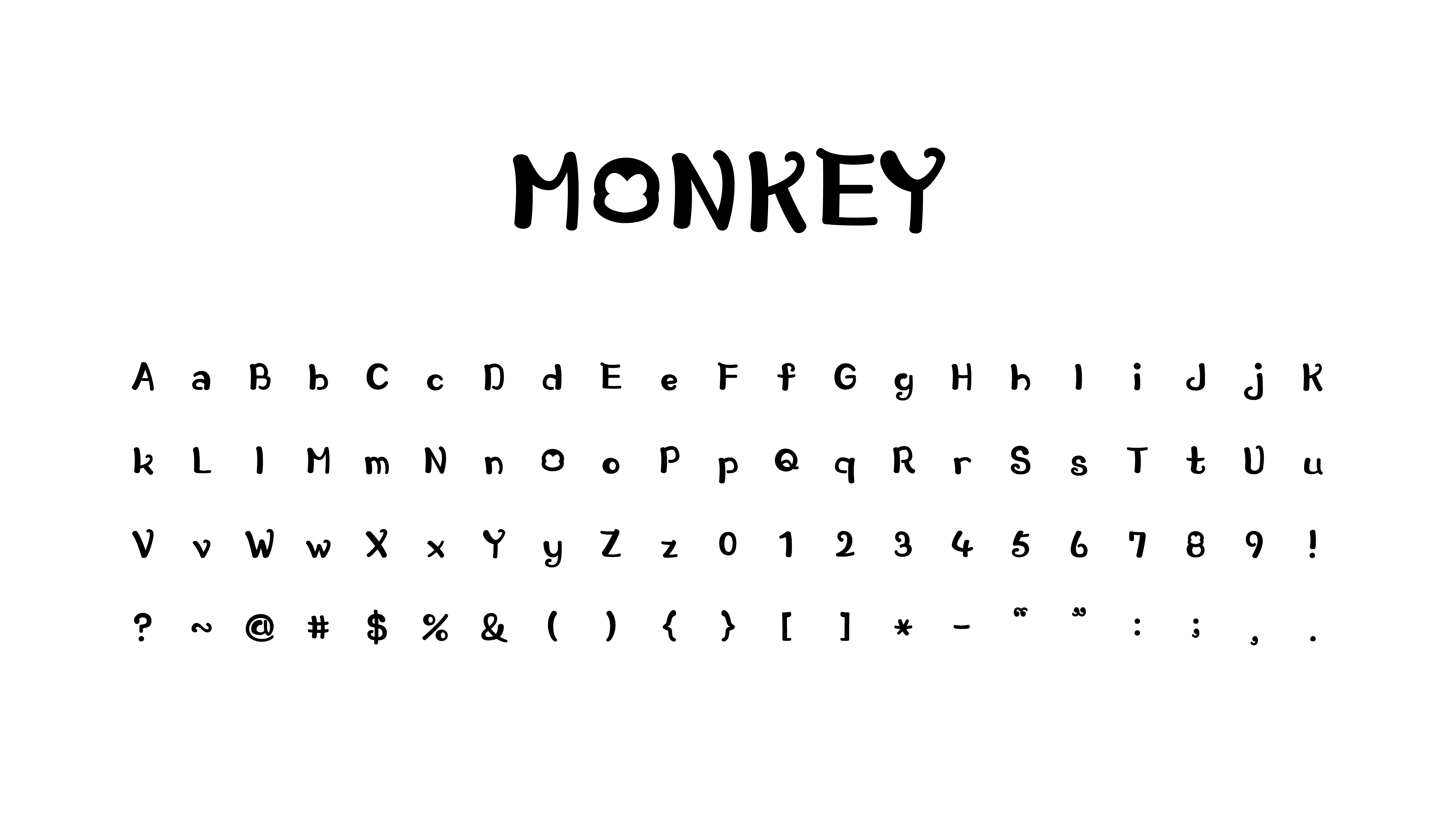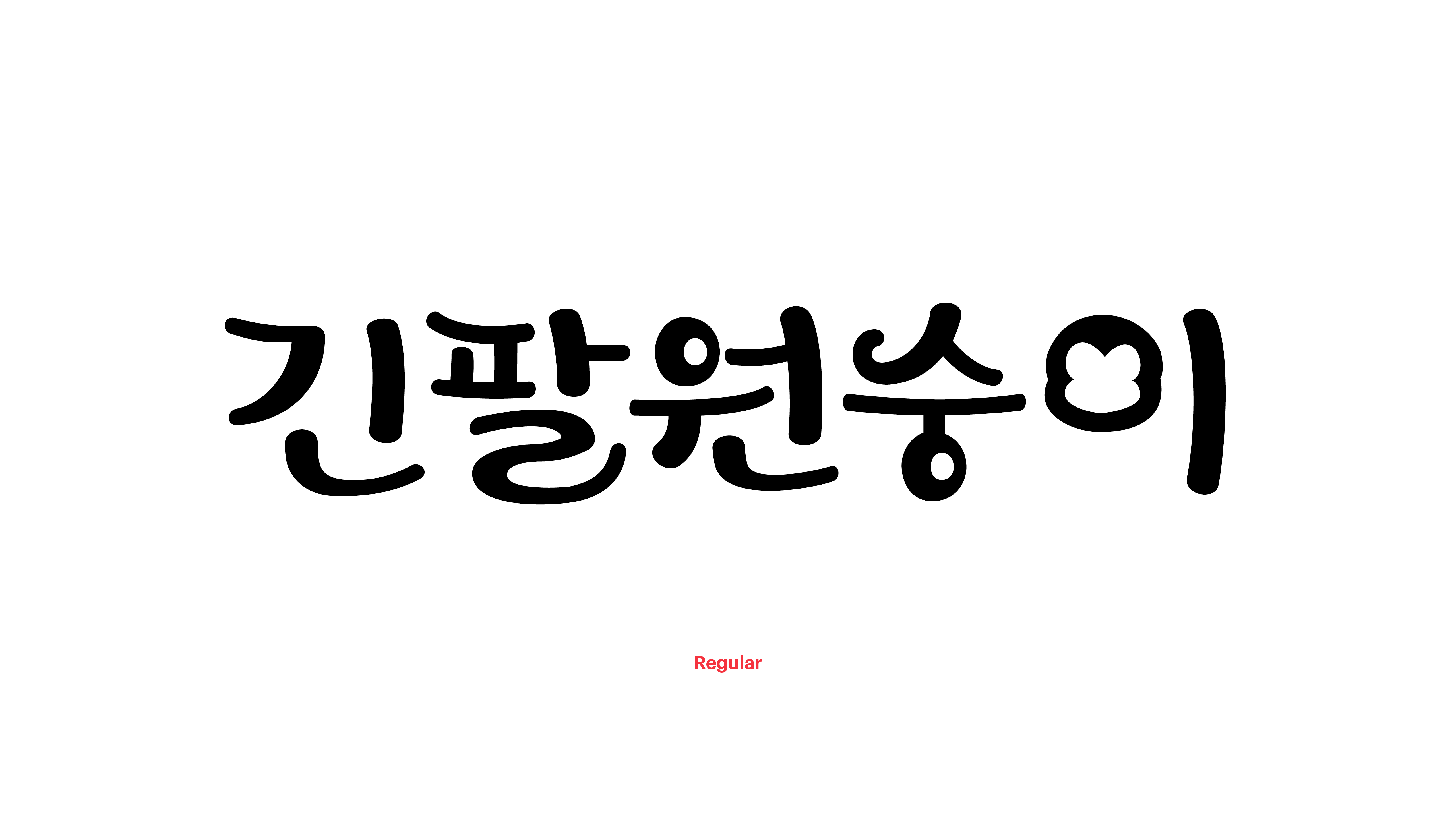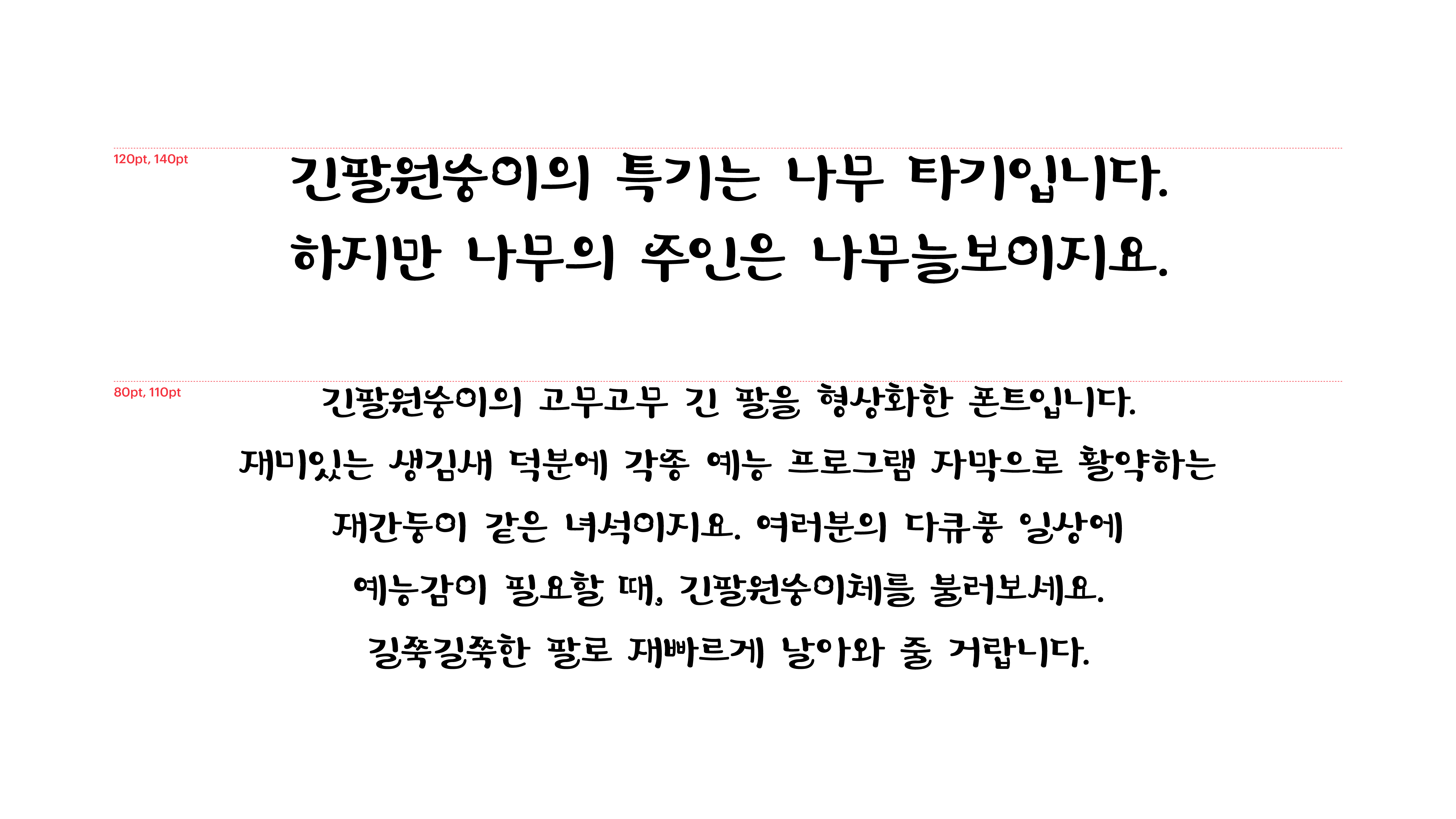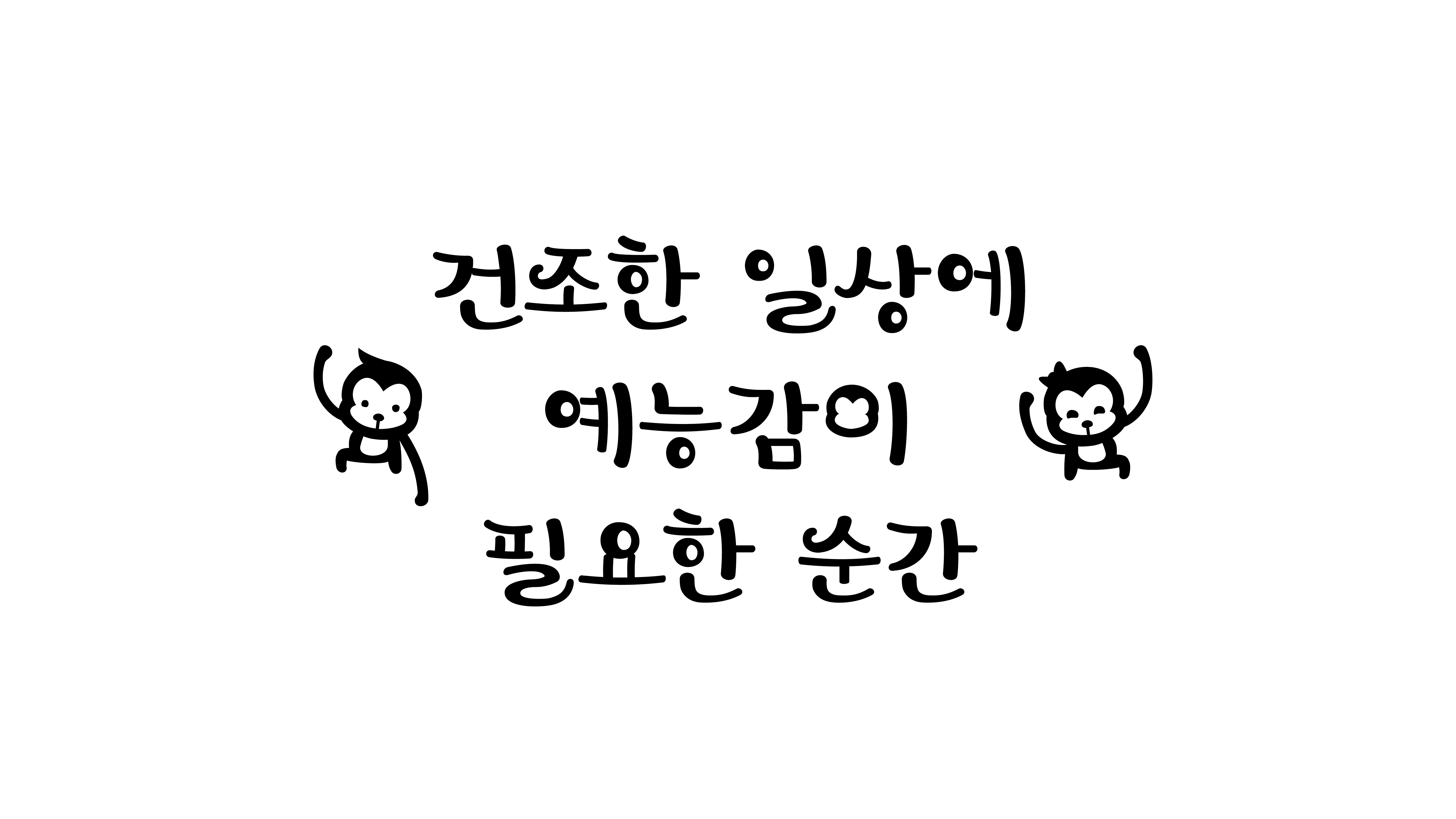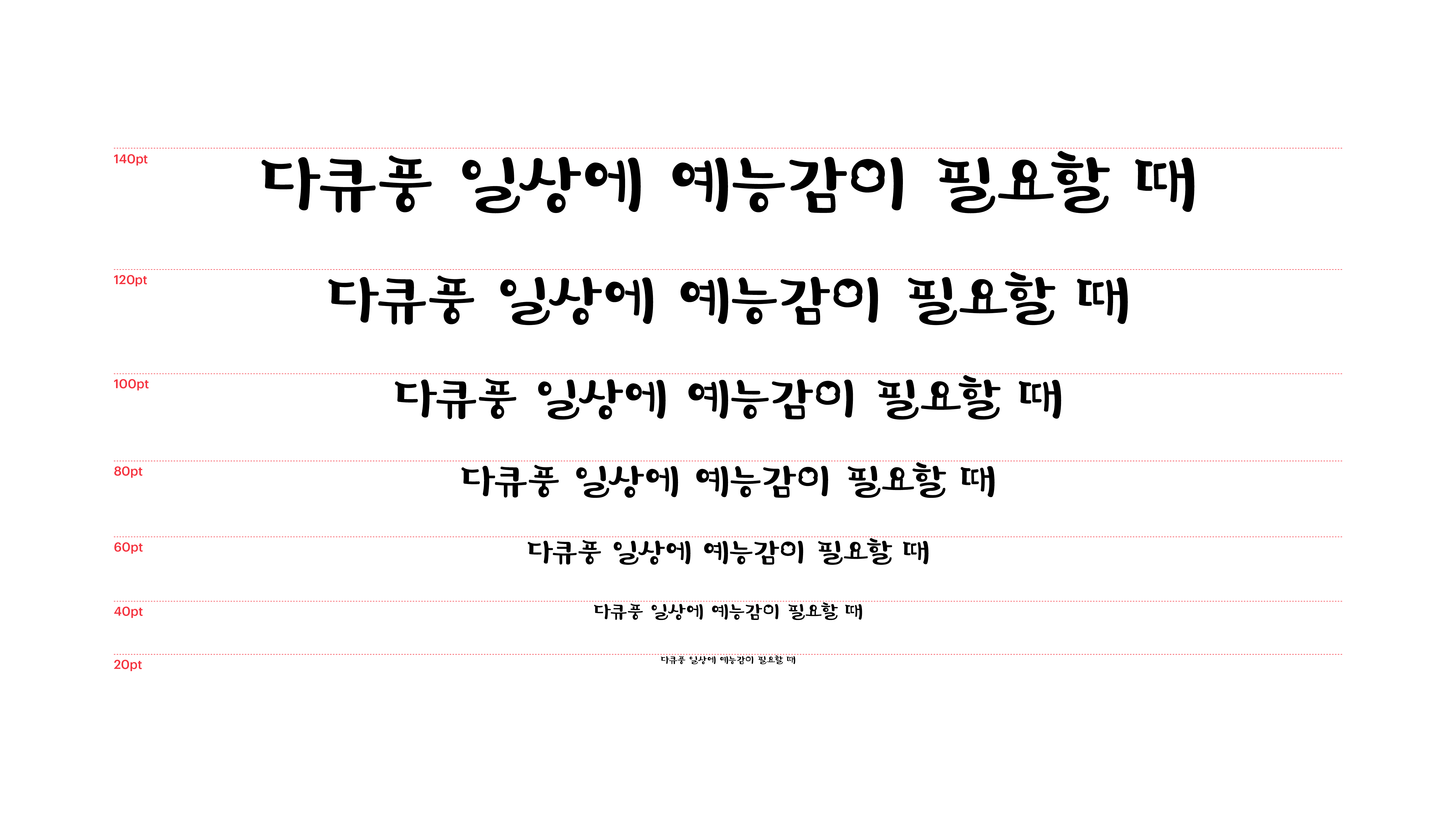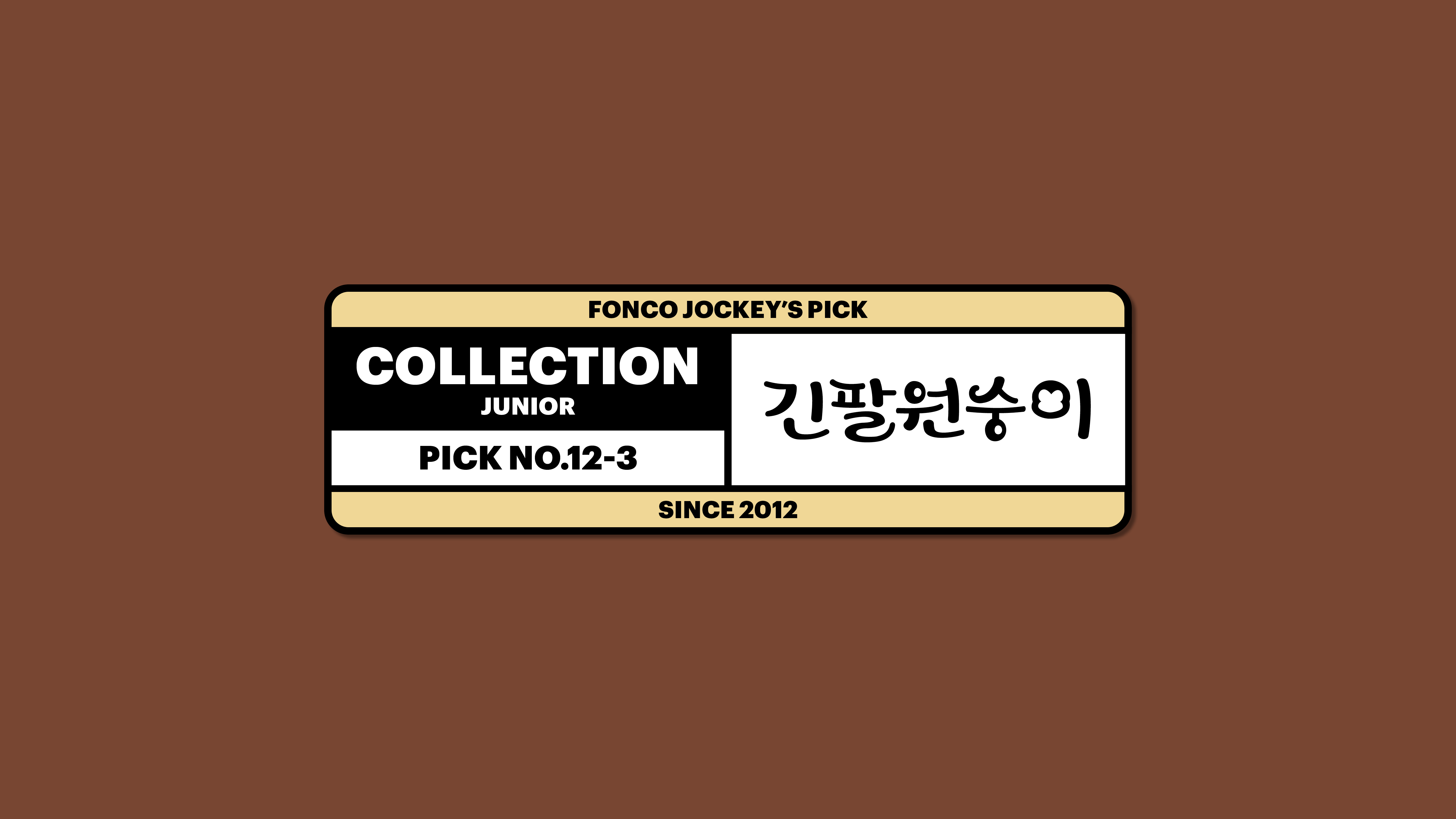
긴팔원숭이
Yoon 긴팔원숭이
긴팔원숭이의 고무고무 긴 팔을 형상화한 폰트입니다. 재미있는 생김새 덕분에 각종 예능 프로그램 자막으로 활약하는 재간둥이 같은 녀석이지요. 여러분의 다큐풍 일상에 예능감이 필요할 때, 긴팔원숭이체를 불러보세요. 길쭉길쭉한 팔로 재빠르게 날아와줄 거랍니다.